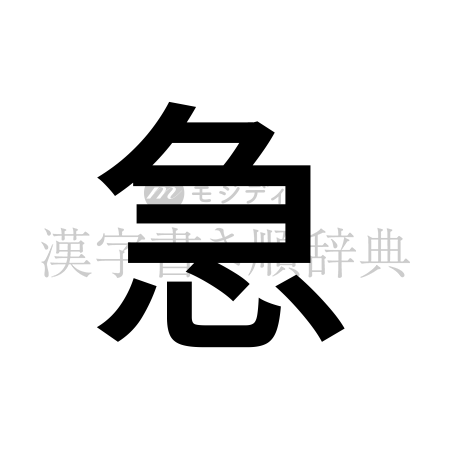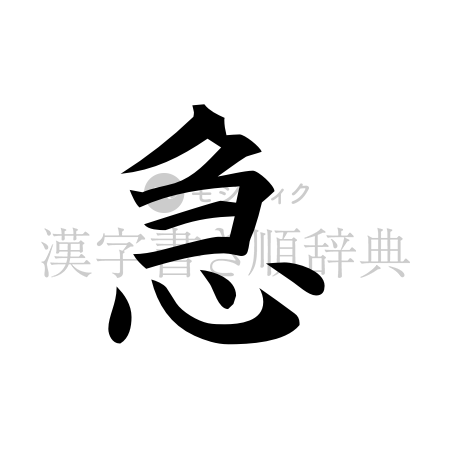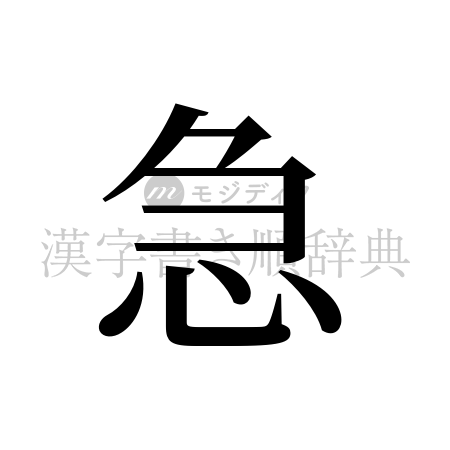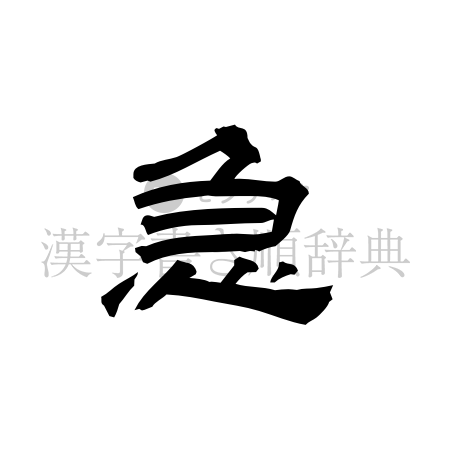
漢字「急」(キュウ)の書き順・読み方・意味・部首・画数
「急」の書体
• 急の書体「ゴシック体」のイメージ
• 急の書体「明朝体」のイメージ
• 急の書体「教科書体」のイメージ
• 急の書体「楷書体」のイメージ
• 急の書体「行書体」のイメージ
• 急の書体「草書体」のイメージ
• 急の書体「隷書体」のイメージ
• 急の書体「篆書体」のイメージ
「急」に形の似た漢字
「急」の意味
• 速やかであること。
• 緊急であること。
• 突然であること。
• 重要であること。
• 急いでいること。
• 急勾配であること。
• 急流であること。
• 急激であること。
「急」の意味の英訳
漢字は1文字で多様な意味を持ちますが、「急」を英語で表す場合、一般的には hurry, emergency, sudden, steep などがあります。
「急」の成り立ち・由来
構造 意符心(こころ)+音符及(きゅう)
「急」は形声文字です。下部の「心(こころ)」が意味を表す意符、上部が音を表す音符で、この上部はもともと「及」の変形した形です。「及」は人に手が届く、追いつくさまを表す字で、「きゅう」という音を担っています。心がせきたてられ、追い立てられるような気持ちを組み合わせて、「いそぐ」「せく」という心の状態を表しました。そこから、速やかであること、緊急であること、突然で激しいさまなど、勢いの強さを示す広い意味へと展開しました。
※ 上部の字源については及の変形とする説が有力ですが、細部には諸説あります。
「急」を含む熟語・単語とその意味
急務 - きゅうむ
急いでしなければならない仕事や任務。
急用 - きゅうよう
急ぎの用件。
至急 - しきゅう
非常に急ぐこと。大急ぎ。
「急」の構成部品
「急」は上に「𠂊」「⺕(けいがしら)」、下に「心(こころ)」を組み合わせた漢字です。
「急」の筆画・ストローク構成
「急」の国語施策